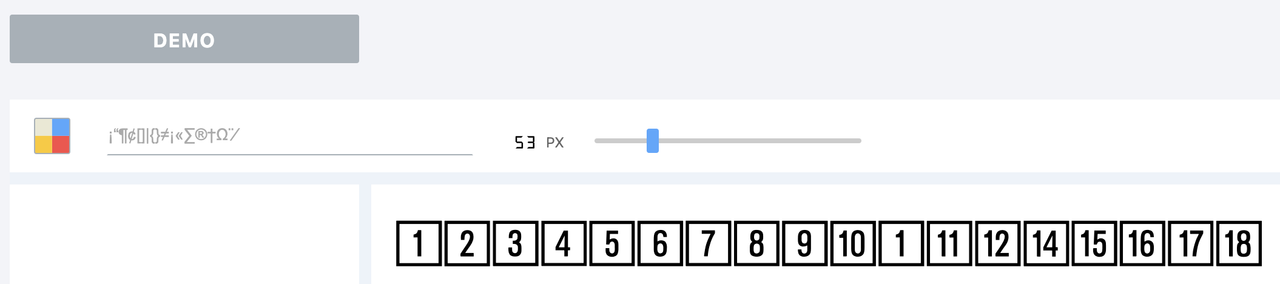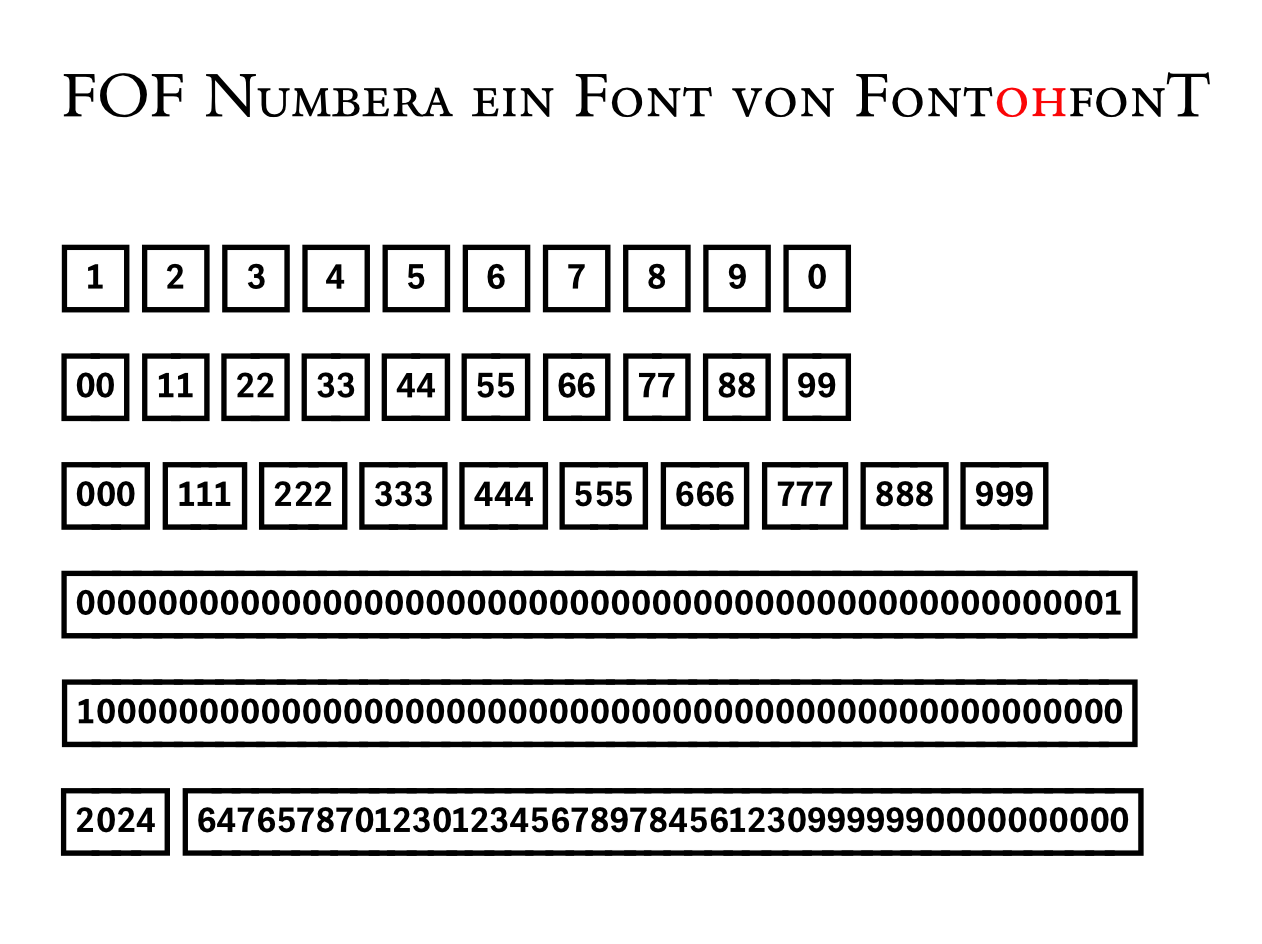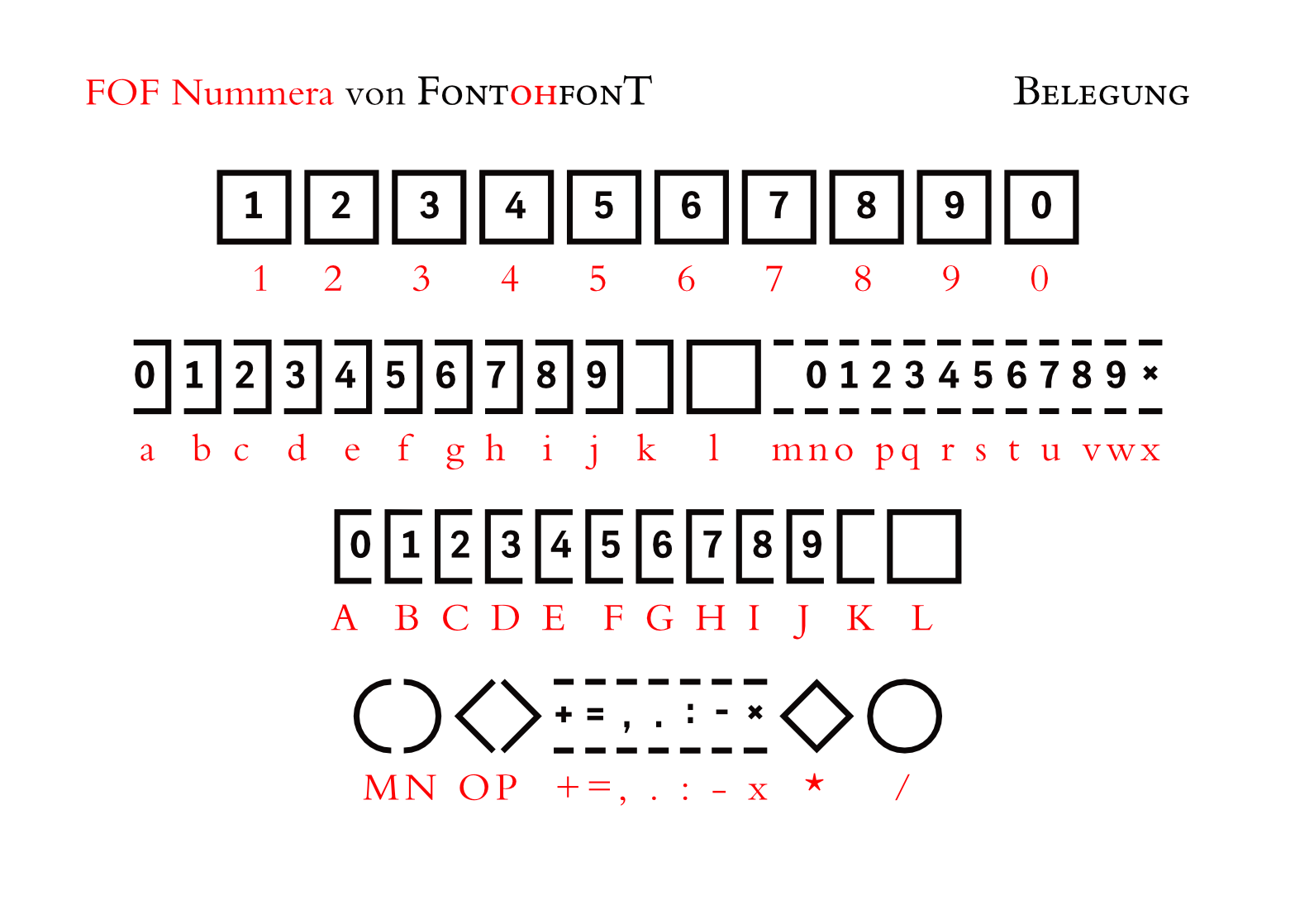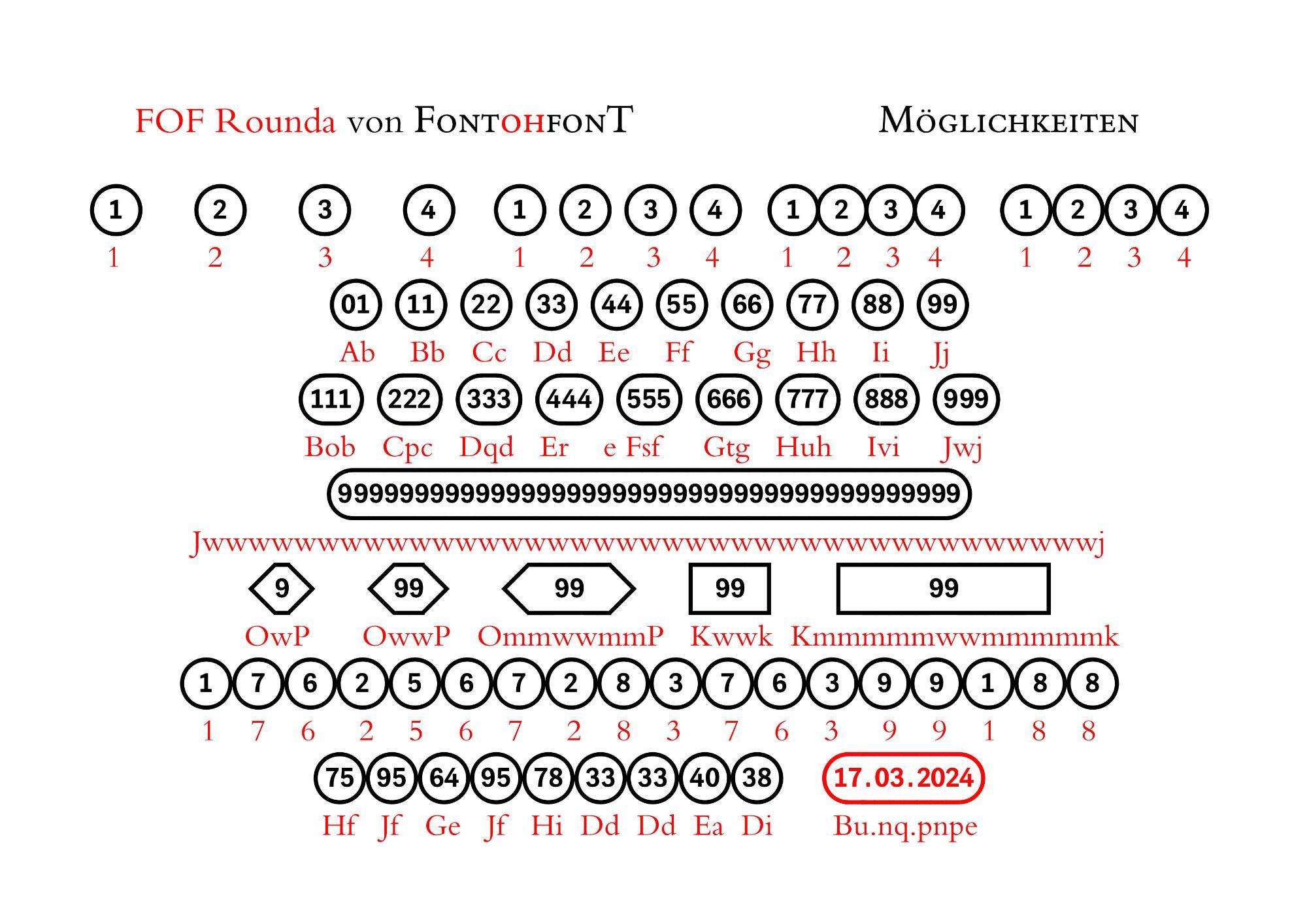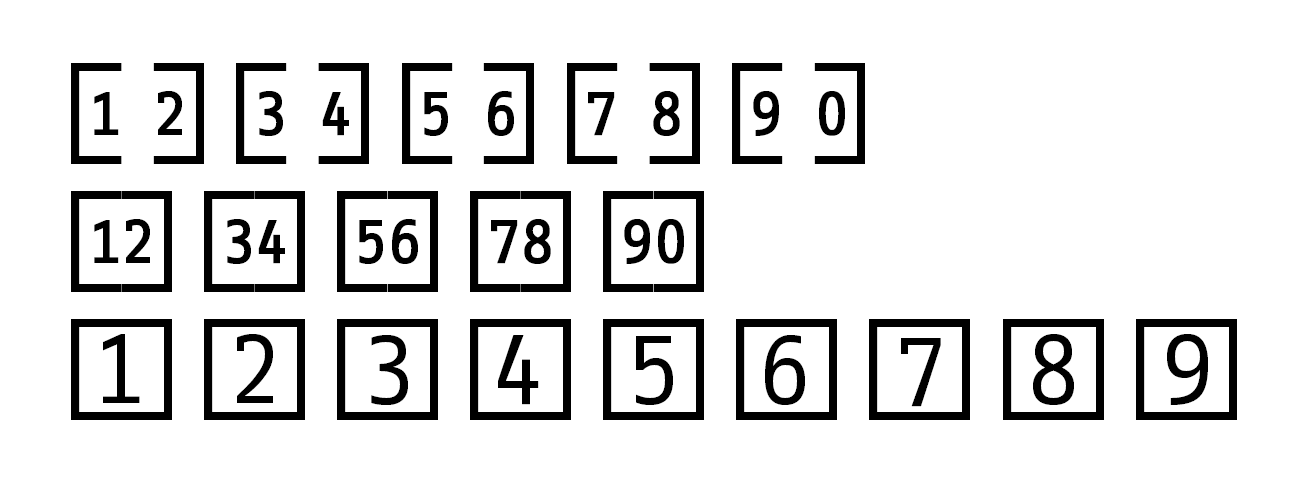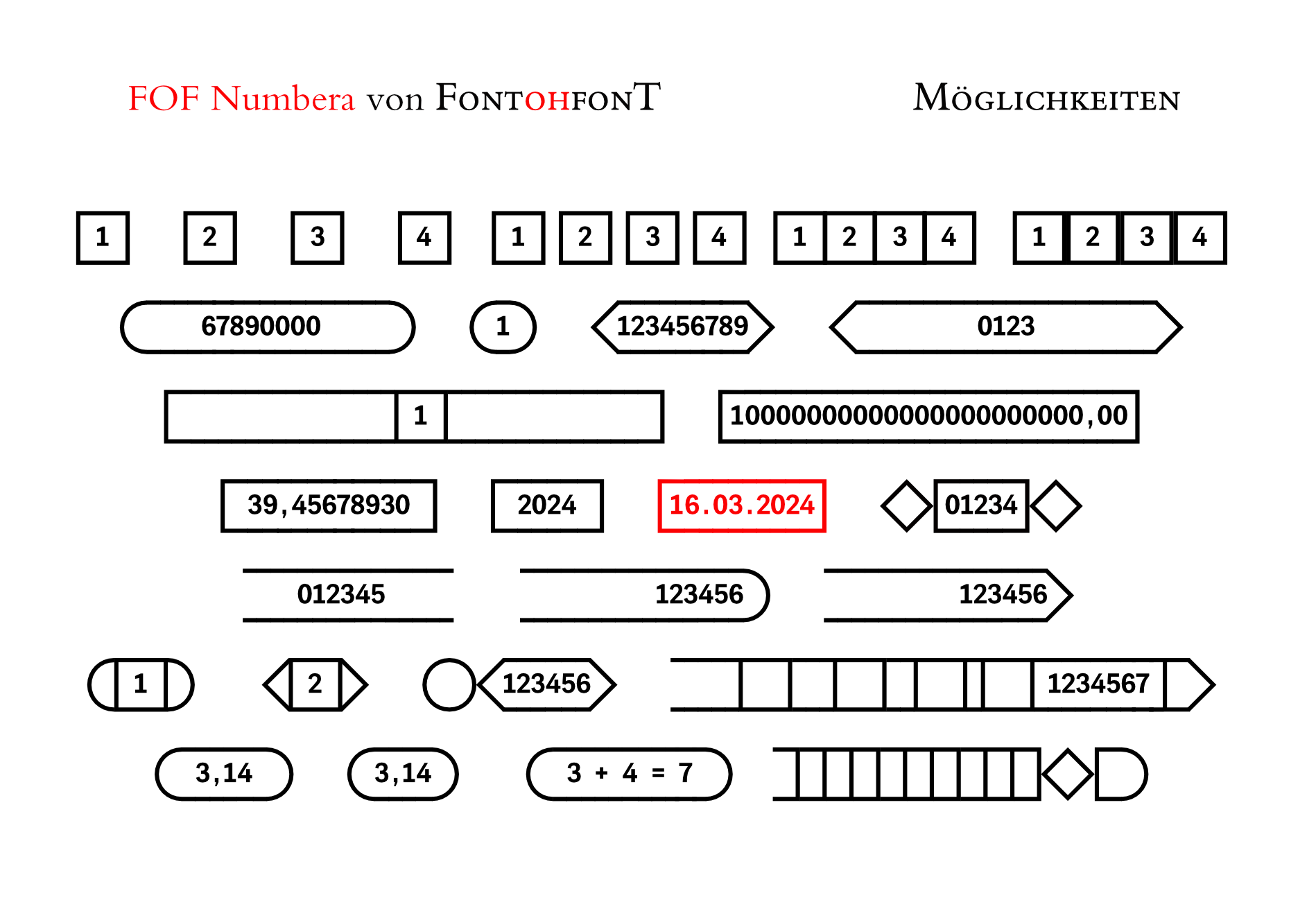
Schrift mit Ziffern im quadratischen Rahmen gesucht
Ich suche eine Schrift, bei der die Ziffern in einem quadratischen Rahmen stehen.
Schon ganz gut finde ich das bei der »FF Info Correspondence Pro Regular«. Allerdings nur die zweistelligen Zahlen. Die einstelligen Zahlen sind leider viel größer.
Vielleicht hat jemand eine Idee. »Bundesbahn Std Pi 1« ist mir zu hässlich.
Um zu verdeutlichen, was ich genau suche, habe ich mal einen Screenshot eingefügt.
In der ersten Zeile sind einzelnen Ziffern durch Leerzeichen getrennt.
Ohne diese Leerzeichen (zweite Zeile) ergibt der Rahmen bei zweistelligen Zahlen ein perfektes Quadrat.
Die einstelligen Zahlen (dritte Zeile) haben dagegen eine deutlich größere Versalhöhe. Wünschen würde ich mir hier eine Zahl in der gleichen Größe mit links und rechts mehr Platz innerhalb des Rahmens.
Ein Sahnehäubchen könnte noch eine mittlere Ziffer für dreistellige Zahlen sein. Das darf dann auch rechteckig werden.
Auf jeden Fall brauche ich Zahlen von 1 bis 99.
unsere neue Serie57 https://www.neue.shop/articles/neue-serie57-type-specimen hat ziffern sowohl im rechteck als auch im kreis, positiv und negativ, aber nur einstellig. Aber es gibt sowohl bei der Serie57 als auch bei der FF Real eckige leere rahmen, mit denen man sich sowas bauen könnte. Ich glaube, dass auch einige schnitte meiner FF Meta und ITC Officina dieses feature haben, kann aber gerade nicht nachsehen.
wenn du die einstelligen ziffern als 01, 02 etc schreiben würdest, hättest du das problem gelöst. Und schau mal bei der FF Transit nach, ob es da solche ziffern gibt. Für die BVG hatten wir sowas für die liniennummern gebaut, aber ich glaube nur im kreis bzw oval und auch dann nur zweistellig. Bin unterwegs mit iPad ohne fonts.
@Lothar B. Was genau möchtest du mit den Zahlen im Rahmen machen bzw. wie werden sie eingesetzt? Je nach Ziel gibt es unterschiedliche Möglichkeiten das zu realisieren …
Von der VEDA-Fontproduktion gab es in den 1990er-Jahren die Fonts
Numbers1 (rund bzw. oval) und Numbers2 (eckig) mit Ziffern sowohl positiv als auch negativ.
Der VEDA-Verlag brachte damals eine Zeitschrift zum Programm Ventura-Publisher heraus, dazu gab es regelmäßig Begleitdisketten mit Fonts und Dingbats, die von den Abonnenten verwendet werden durften. Der Verlag existiert schon lange nicht mehr. ich habe die beiden Fonts (Postscript) immer noch auf meinem Rechner. Die Ziffern lassen sich endlos zusammenstellen.
cooler scheiß! Wie kann ich den kriegen? Und woher sind die ziffern? Sehen nach Franklin Gothic aus. Sehr schön.
Nix Franklin Gothic. Habe ich vor Jahren selbst gemacht. Wollte mal eine Schrift entwerfen. Ist brotlose Kunst.
Am Font muß ich noch was ändern. Die Zahlen stehen zu hoch.
Das ist mir auch aufgefallen. Sonst aber in der Tat vielversprechend. Gibt es da auch noch ein passendes Alphabet dazu oder beschränkt sich das Ganze auf Ziffern?
Mit einem Alphabet, das muß ich mal überlegen ob das funktioniert.
Gegenwärtig arbeite ich an einem reinen Kreisfont.
Also Kreis statt Quadrat.
Der FOF Rounda ist auch geschafft.
Also nun auch Zahlen bis 99 im Kreis. Wenn es mehr sein muß, also ab 100, dann wird es wurstartig.
Einen kostenlosen Font habe ich gefunden: »Concourse Index«. Anscheinend mit einer interessanten Ligatur-Lösung.
Die »Profile« von Supertype werde ich kurz ausprobieren. Eventuell muss ich dann die Ziffern in Weiß anlegen und mit einer schwarzen Kontur versehen.
Immerhin ist die Schriftart bei den Adobe Fonts schon mit dabei.